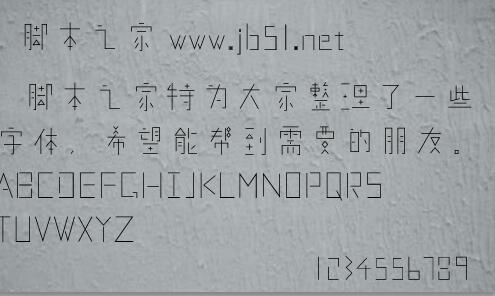
佛君城建體簡以線條為緣起,以抽象幾何手法,構(gòu)筑極簡唯美的城市建筑意象,除橫平豎直的基礎(chǔ)表現(xiàn),融入45度斜角展開的線條,在保證識別性的基礎(chǔ)上減化筆畫,歸納出易于表現(xiàn)為幾何造型的結(jié)構(gòu),形成結(jié)構(gòu)獨特、識別效果突出、極具時尚感的字型,契合互聯(lián)網(wǎng)時代個性鮮明的傳達(dá)需求,提供獨具一格的視覺傳播解決方案。